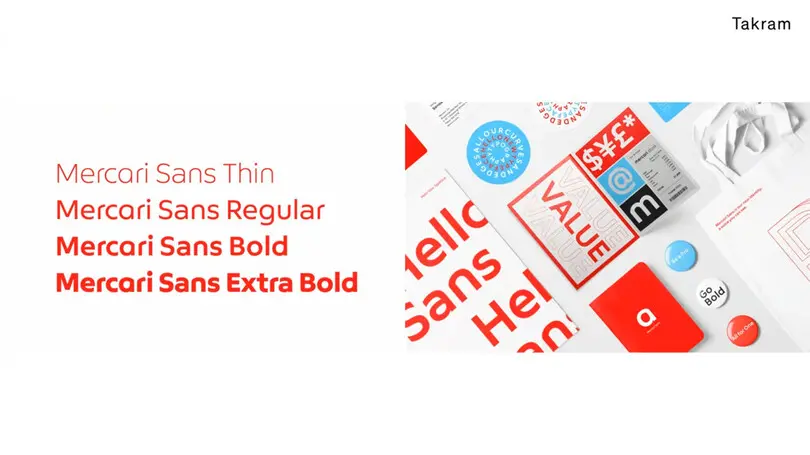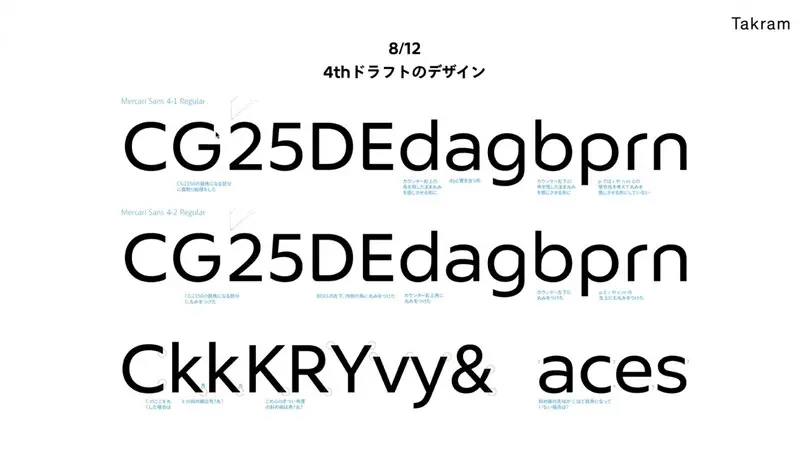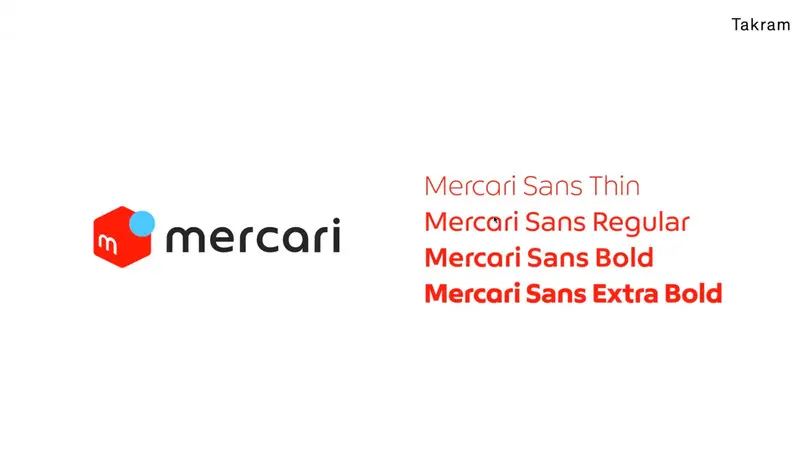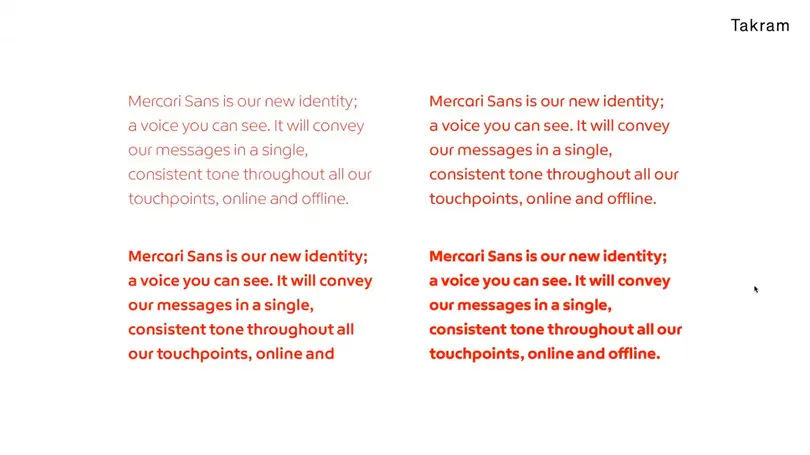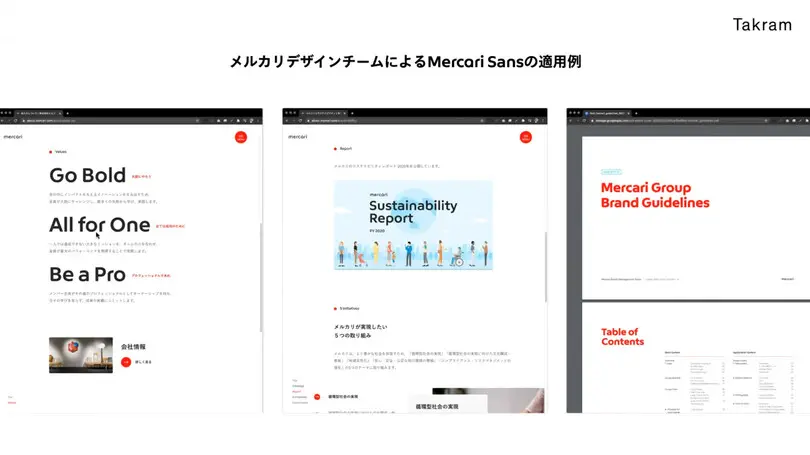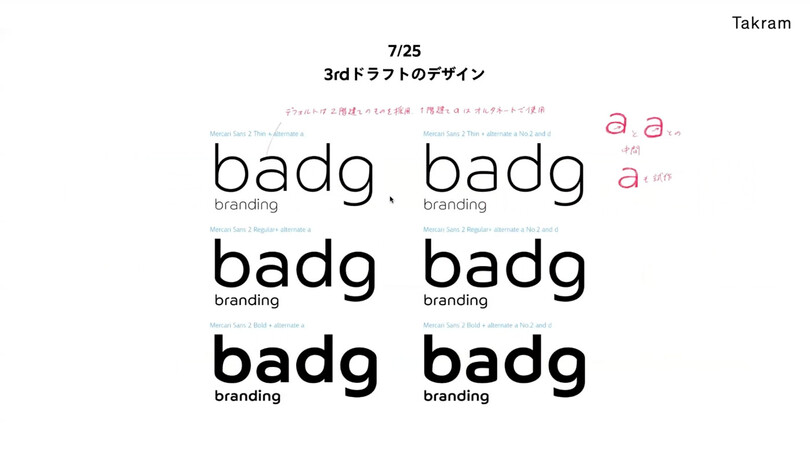
コーポレートフォントの制作と
ブランディング Mercari Sansの事例
フリマアプリ「メルカリ」を運営する株式会社メルカリのコーポレートフォント(専⽤書体)制作について。同社の社内デザインチーム、デザイン・イノベーション・ファーム Takram(タクラム)、Monotypeの3社でどのようにコーポレートフォントを制作したのか、そのプロセスを具体的に紹介。
前半は、Takramアートディレクターの弓場太郎氏が書体制作の概要とプロセスを紹介。プロジェクト開始からフォント完成まで、図版を⾒ながら解説しました。
コーポレートフォント制作のきっかけとなったのは、2018年のロゴリニューアル。その時のキーワードは、ワクワク感、公平さ・オープンさ、なめらかさ。このキーワードをもとにTakramがロゴタイプを、Takramとメルカリデザインチームが一丸となりシンボルをリデザインし、既存のフォントでコーポレートフォントを暫定的に設定。和⽂書体は、たづがね⾓ゴシック、欧⽂書体はFF Markが指定されました。
コーポレートフォントができるまでは、この2つのフォントを暫定的に使っていたのですが、既存のフォントの組み合わせではメルカリらしさが表現できないという問題や、メルカリのコーポレートロゴと並べて使用した際に生じる世界観の違い、特定の欧⽂書体と和⽂書体を混植できる環境が限られるという問題がありました。
⼀貫したメルカリらしさを伝えるためには、既存のフォントではなく、⾃分たちのオリジナルフォント、つまりコーポレートフォントを新しく作る必要があるのではないか。コーポレートフォントを使うことで企業のらしさを最⼤限に⽣かした、⽬に⾒える声としての書体を表現することがブランディングにつながるのではないか。そうした考えから、コーポレートフォントの制作がスタートしました。
オリジナルフォントの制作は、メルカリのデザインチーム、Takram、Monotypeの3社で進めることに。和⽂書体には、たづがね⾓ゴシックを使うので、そのデザインに関わったMonotypeタイプディレクター、⼩林章と⼀緒にオリジナルの欧⽂書体を新しく作るのが最善ではないかということになりました。
初回のキックオフは、2019年2⽉。ドイツ在住の⼩林と遠隔会議を通じたディスカッションを⾏い、「トラスト(安⼼、信頼)」と「オープン(公平さ、親しみやすさ)」というデザインの⽅向性を確認しました。
制作の要件としては、
• ⽇本語はたづがね⾓ゴシックをベースに使う
• たづがね⾓ゴシックとマッチした欧⽂書体を作る
• 新サービスのロゴ展開に使えるようにメルカリロゴタイプとマッチした欧⽂書体を作る
が挙げられました。
また、コーポレートフォントの⽤途として、コーポレートWebサイト、印刷媒体、IR資料、広告、Mercari〜という新しいサービスが登場した際のロゴなどに使いたいという話がメルカリからありました。
初回のドラフト3案が⼩林から提案されたのは 2019年 6⽉11⽇。「mercari」の各⽂字のほか、⼤⽂字Gや⼩⽂字lの形も検討されました。⼩⽂字mは左側の縦棒がある形状と縦棒がない形状、⼩⽂字aの形は 3種類、⼩⽂字eやcの切り⼝の⾓度は垂直、斜め、さらに斜めというように、それぞれの⾒え⽅を⽐較。最初は特定の案に絞り込まず、なるべく広く、いろいろな形を検討しながら、⽅向性を探っていきました。その結果、⼀つ⽬の案と⼆つ⽬の案の中間をさらに突き詰めることに。
7⽉25⽇に提出された3回⽬のドラフト。メルカリのロゴタイプにおいては、上に線がない⼀階建てのaが使われていますが、この時点では、⼀階建てと⼆階建てのaの両⽅が検討されています。読みやすさを考えると⼆階建てのaを優先して採用したいのですが、「mercari」と⽂字を打った時にはロゴタイプで使われている⼀階建のaを使いたいため、どちらのaのデザインも残すことになりました。
8⽉12⽇に提出された4番⽬のドラフト。この時は先端のカットの処理について話し合いました。たとえば、⼤⽂字Gや数字2の始筆部を縦にカットすると先端が尖りシャープすぎる印象になってしまうため、ここでは先端に面取り処理をすることで、シャープさを和らげる調整をしました。
8⽉後半に提出された5番⽬のドラフト。⼩⽂字dgbpの中の空洞がやや斜めに⾒えるために⽂字全体が傾いて⾒えるという問題が指摘されました。⽂字が傾いて⾒えないように細かい調整をしました。
毎回、⼩林のデザインをオンラインで画⾯共有しながら、チーム全体でディスカッションを重ねました。⼩林が画⾯上でデザイン修正しているところを全員で⾒ながら⽬指す⽅向を模索。その途中で求めている形が⾒つかった時には、チーム全体が「これだ!」と、どよめいた瞬間もありました。
通常の⽂章を打った時には読みやすい⼆階建てのa、「mercari」と打った時は⼀階建てのaが⾃動的に表⽰されます。このように⽂脈に応じて、異なる形の書体に⾃動変換される機能を「コンテクスチュアル・オルタネート」と言い、今回のコーポレートフォントにも搭載されました。
最終的に、たづがね⾓ゴシックとの混植の確認やフォントデータの調整をして、2019年10⽉にメルカリのコーポレートフォントMercari Sansが完成し、Thin、Regular、Boldの3ウェイトを発表しました。その後、2020年2月に開催したMercari Conferenceに合わせてExtra Boldを追加し、現在は4つのウェイトとなっています。Mercari Sansは現在、メルカリの Webサイトをはじめ、ブランディングのあらゆるシーンで使われています。
前半の最後に、コーポレートフォントを作るメリットが挙げられました。
1. ブランドの声を反映した独⾃のデザインによる他社との差別化
2. 制定書体の統⼀と使⽤を効率化(たづがね⾓ゴシックと Mercari Sansを組み合わせて⼀つの書体にできる)
3. ノンデザイナーの資料にもデザインコントロールがきく(Mercari Sansがインストールされていれば、打つだけできれいな書体の組み合わせが出てくる)
4. コーポレートロゴを展開したサブロゴを作成する際、統⼀感を維持したまま、作業、デザインコストを削減できる。
5. 企業がデザインに投資する取り組みとして、内外へ発信することができる
6. ライセンスのスケールメリット(自社フォントを作成することで、ライセンス管理の選択肢が広がる)
• コーポレート書体を作ることで、企業の声や「らしさ」を統⼀的、効率的に伝えることができる。
• コーポレートロゴとコーポレート書体の親和性が強いほど、両者の統⼀感は強化され、広くブランディングに活⽤できる。
後半は、プロジェクトを担当した Monotypeタイプディレクターの⼩林が加わり、企業のブランディングにおけるコーポレートフォント導⼊のメリットや影響について、話し合いました。
今回の書体制作では、制作メンバーがオンライン画⾯でデザインを共有しながら、その場で細かいところまで意⾒を出し合ったため、非常に進めやすかったそうです。プロジェクト開始から書体完成まで数ヶ⽉くらいでまとまり、⼩林が今までに関わったコーポレートフォントの中でも短期間で、しかも完成度が⾮常に⾼い例の⼀つになったとのこと。
⽂字の細かいディテールを⼀緒に追求していくことよって、チームが⼀丸となってまとまっていきました。プロジェクトが始まる前にはチームの誰もが予想していないかったことですが、コーポレートフォントを作るこのプロセス⾃体が、企業の強みやらしさを⾒つけ、新しいものを⽣み出すパワフルな取り組みとなったのです。
この後、前半のセッションで弓場氏が挙げたコーポレートフォントを作るメリットを、弓場氏と⼩林とで振り返りました。
ここから質疑応答です。
コーポレートフォントの制作をメルカリに提案したのは弓場さんでしょうか? すぐ承認されたのでしょうか?
(弓場氏)最初にメルカリのロゴデザインをする時、「コーポレートフォントも作りましょう」と提案しました。コーポレートフォントがあれば、ブランドイメージの統一を図りやすかったり、一貫した企業の「らしさ」を目に見える声として届けることができます。その後も機会があるごとにメルカリのデザインチームにも提案をし、1年くらい経った頃にコーポレートフォントプロジェクトを始められる準備が整いました。
メルカリとしても、オンライン/オフライン双方のタッチポイントが増えていく中で、ブランドイメージの統一や一貫したメルカリらしさをどのように伝えていくかを考えていたタイミングで、目に見える「声」としての文字がとても重要だと考え、デザインへの投資としてコーポレートフォント制作に至りました。
(⼩林)ロゴの段階からコーポレートフォントを準備していたというのは初めて聞きました。ロゴは新しくなった時は注⽬されますが、だんだんと注⽬度は落ちていきます。しかし、企業が発信するメッセージは、その都度、新しく送られます。ロゴとコーポレートフォントの両⽅で相乗的にメッセージを伝えられるというのはとても⼤事なのではないかと思います。
⼩林さんに質問です。コーポレートフォントを作る時の⾯⽩さはどこにありますか? Monotypeの書体を作る時と⽐較して、何か違いはありますか?
お客様との話し合いを通して、⾃分でも予想していなかったデザインになったり、スタート地点にいた時は思ってもみなかった解決策になっていったりすることです。打ち合わせの時にお客様の反応によって、ぴったりの形が⾒つかり、「きた!」という瞬間があります。そこが⾯⽩いところだと思います。